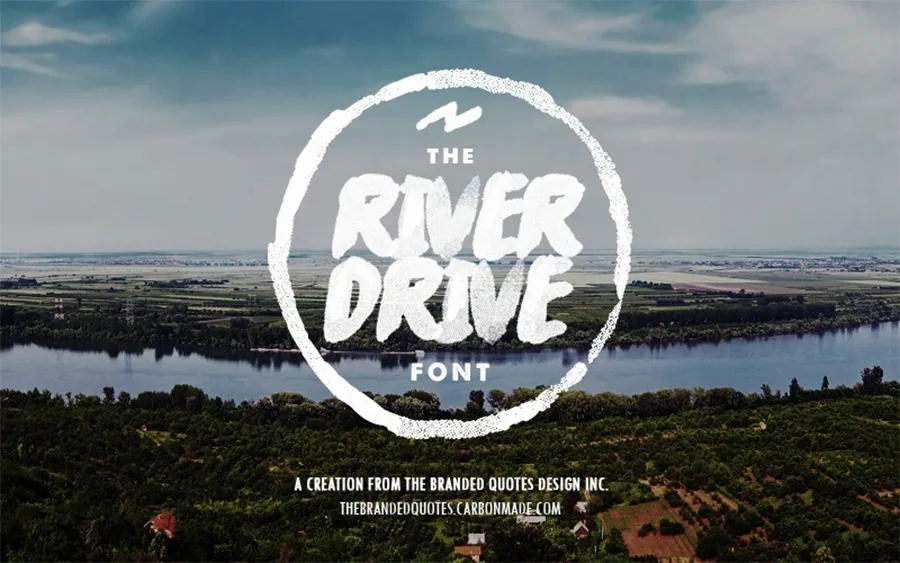
A fonte ‘River Drive Font’ é uma criação inovadora que combina elementos modernos de tipografia pincelada com o estilo urbano da tipografia das ruas, resultando num look fresco e úmido como se fosse uma substância nova aplicada. Especialmente atraente para designers gráficos, este tipo de fonte apresenta cada caractere cuidadosamente criado, gerando um conjunto perfeito de letras que oferece um visual despretensioso e profissional. Ideal tanto para aplicações interativas quanto para uso mais formal, ‘River Drive Font’ é uma escolha excepcional para quem busca criar designs contemporâneos em brush fonts. Inspirada no trabalho do designer Hamilton, esta fonte é uma novidade na categoria de brush fonts que certamente impressionará sua audiência com seu visual único e sofisticado ao mesmo tempo.